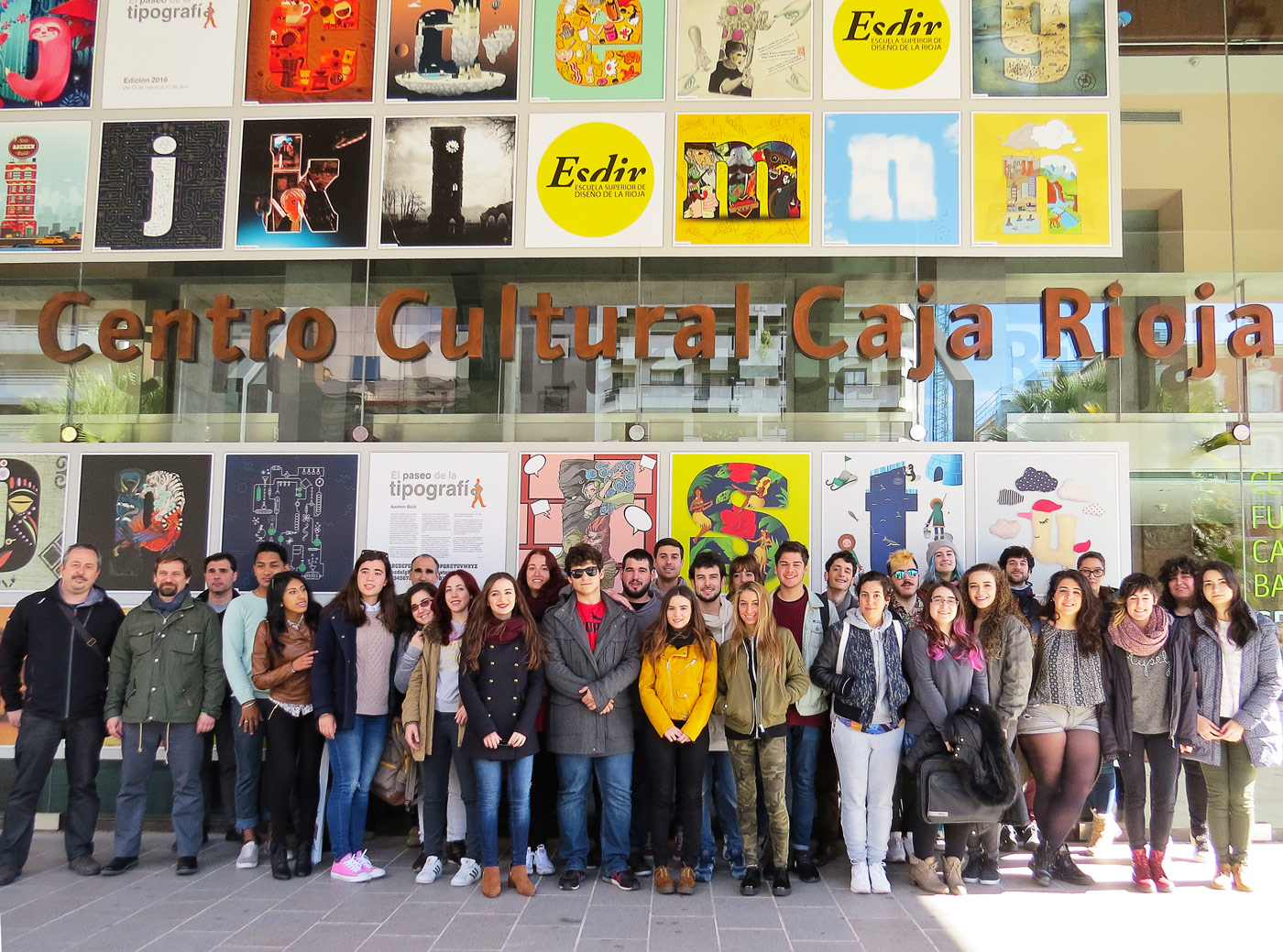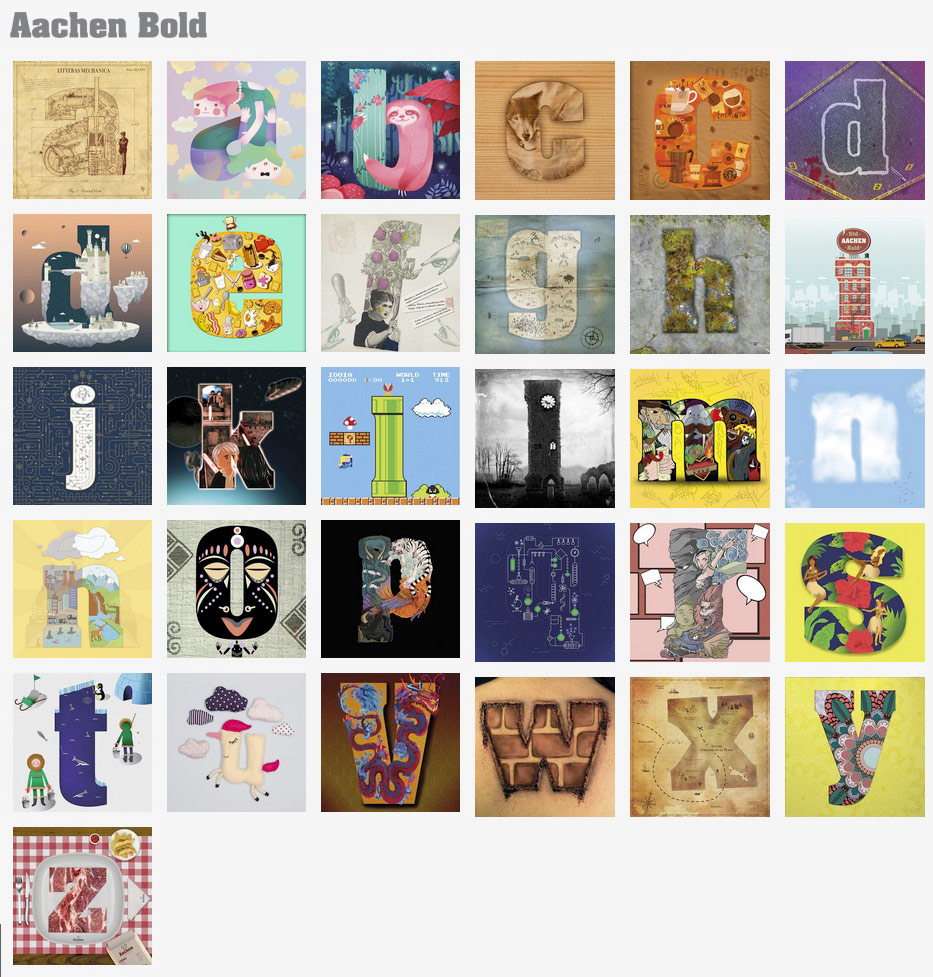
El Paseo de la tipografía edición 2016 esta dedicado este año al alfabeto Aachen Bold, y los alumnos de segundo de Grado en Diseño Gráfico de la ESDIR dentro de la asignatura de Tipografía 2 han desarrollado diferentes intervenciones gráficas sobre las letras de caja baja de esta tipografía, dando lugar a letras iniciales ornamentadas donde predomina la fantasía y la creatividad personal mediante la experimentación de diferentes técnicas y estilos de ilustración y fotomontaje.
Los alumnos de segundo curso han desarrollado nuevamente un magnífico trabajo que ha podido verse en las cristaleras del Centro cultural Cajarioja situado en la Gran Vía del Rey Juan Carlos I del 23 de marzo al 17 de Abril.
Aachen (Aquisgrán en alemán) era el nombre de la residencia imperial de Carlomagno en el siglo VIII y en cuyo scriptorium el monje Alcuino Flaco de York creó una de las primeras caligrafías normalizadas de la historia destinada a solventar los problemas de comunicación de tan vasto imperio. Sin embargo esta robusta letra nacida para titulares, y actualmente muy utilizada en ámbitos deportivos, caracterizada por tener terminales acartelados, poco tiene que ver con los alfabetos medievales del escritorio de Carlomagno. Se trata pues del rediseño de una egipcia suave, no del XIX sino de principios del XX. Mecana según el sistema AtypI Vox de catalogación de tipos dentro de los estilos llamados clarendons o jónicos subcategoría del estilo Antique. Registrados como clarendons por primera vez por Robert Besley en 1845 aunque ya existían desde 1810. Estas letras están dotadas de configuración formal enormemente popular en el contexto de la revolución industrial, coincidente con el incipiente desarrollo de una industria publicitaria aún muy rudimentaria y necesitada de nuevos tipos con que rotular todo tipo de mensajes y productos.
Sus autores, los diseñadores ingleses especializados en el dibujo de tipos Alan Meeks y Collin Brignall, realizan esta versión en 1969, que será posteriormente ampliada en 1977 con el desarrollo de los pesos medios de la familia tipográfica.
Collin Brignall trabajó como dibujante, tipógrafo y fotógrafo profesional de moda llegando en 1980 a presidir la empresa Esselte Letraset, lider en la producción de alfabetos transferibles en seco, justamente en el mismo momento en que se lanzan al mercado los computadores Apple MacIntosh que supusieron precisamente el declive de estas técnicas de autoedición analógica.
Allan Meeks por su parte trabajo para la empresa Esselte realizando numerosos alfabetos y posteriormente para Internacional Typeface Corporation ITC trabajando actualmente como free-lance especializado en la customización de fuentes corporativas.
Actualmente Aachen es suministrada por la empresa norteamericana Monotype fundada por Robert Lanston en 1887 y reconvertida en fundición digital a partir de su absorción por Afga-Compugrafic en 1994.
Fruto de la colaboración entre Monotype Studio e ITC y del trabajo conjunto entre los diseñadores Alan Meeks, Collin Brignall y el tipógrafo norteamericano Jim Wasco (chef, músico de jazz y fabricante de cerveza casera) aparece en el año 2012 en los mercados tipográficos Neue Aachen, una revisión donde se desarrolla la familia completa con alfabetos inclinados e incluso ultrafinos, con remates muy sólidos, pero considerablemente más cortos que las de su precursor y todo tipo de adaptaciones que permiten los archivos .otf respecto a nuevos glifos para diferentes alfabetos no latinos.